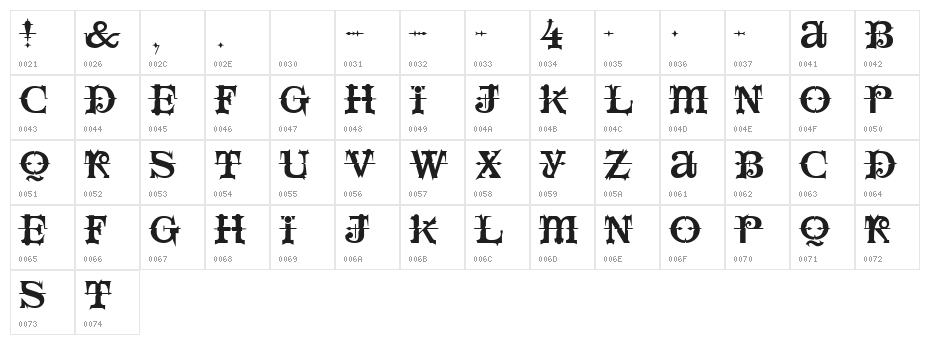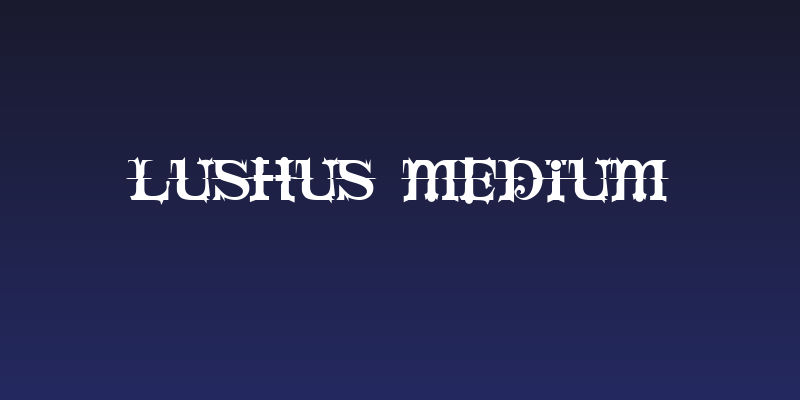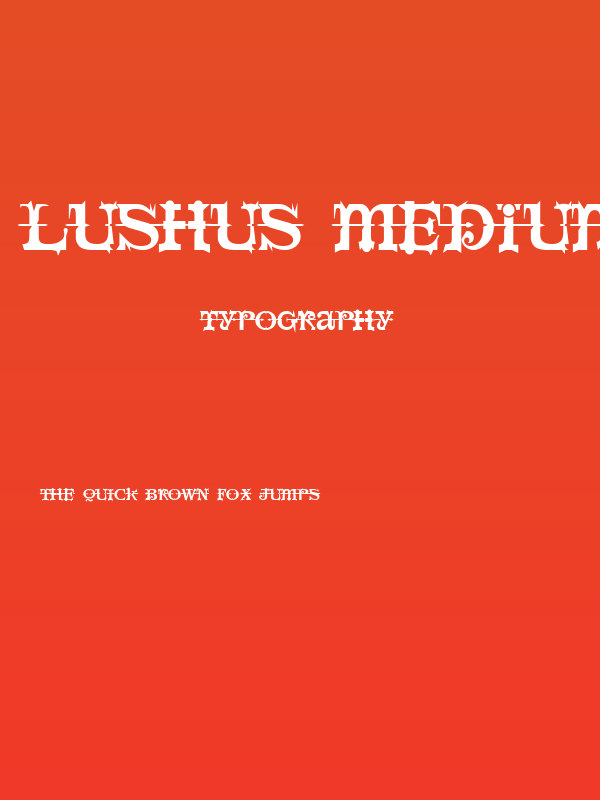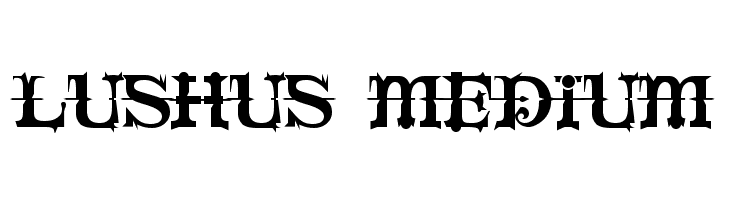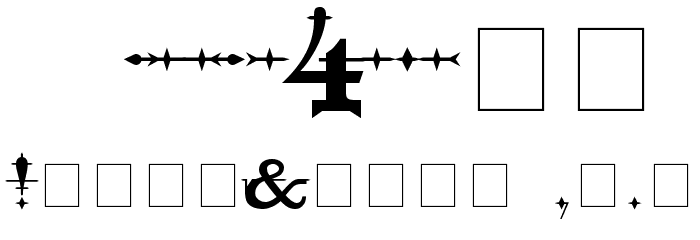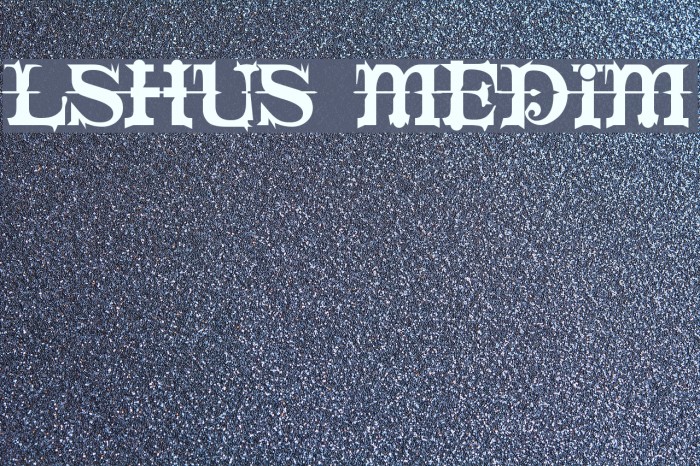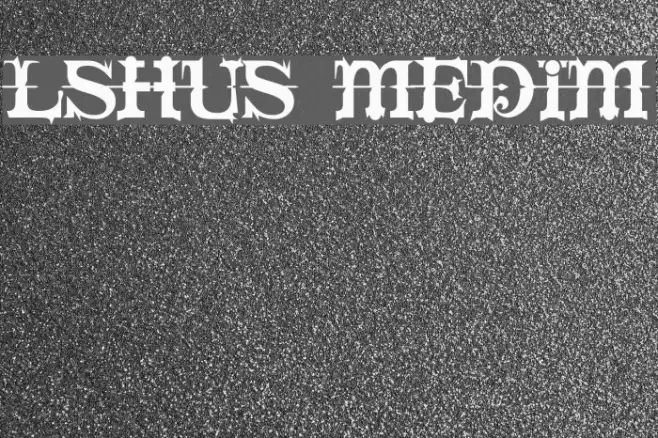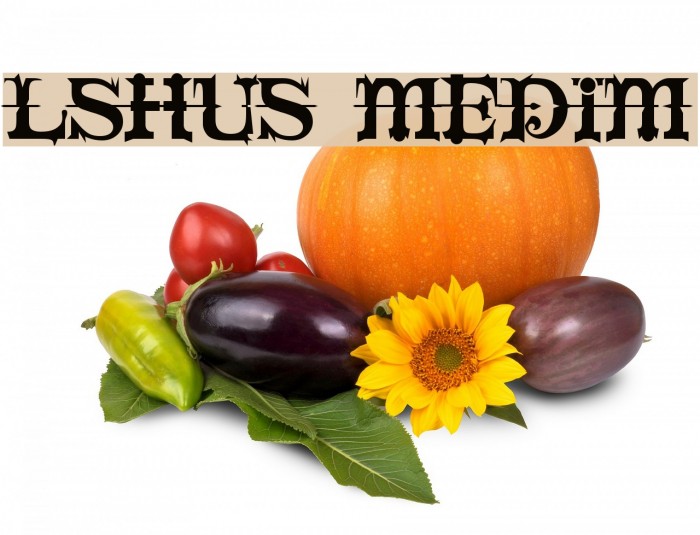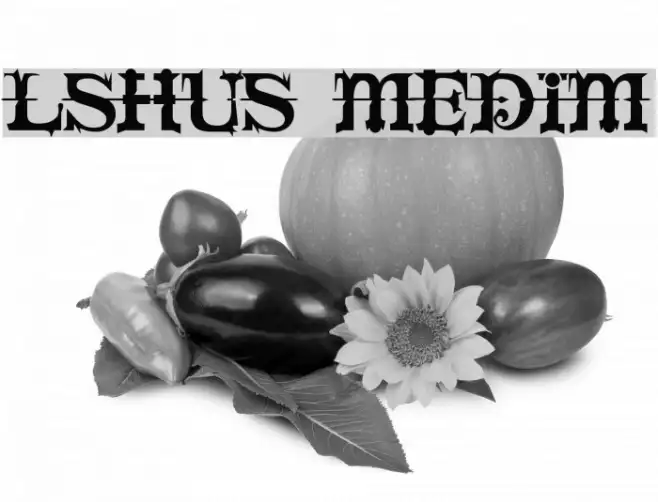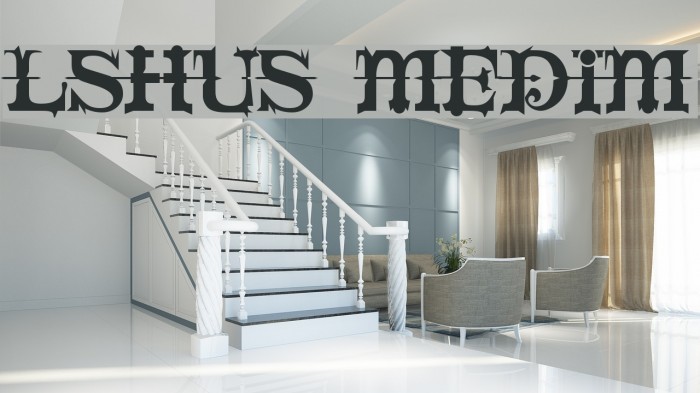
LushUs Medium Font
Questo font include 69 caratteri. Clicca su un carattere per vedere i dettagli.
| Stile generale | Gothic, Decorative |
| Progetti proposti | Ideal for album covers, posters, branding for edgy or alternative products, and any design needing a dramatic flair. |